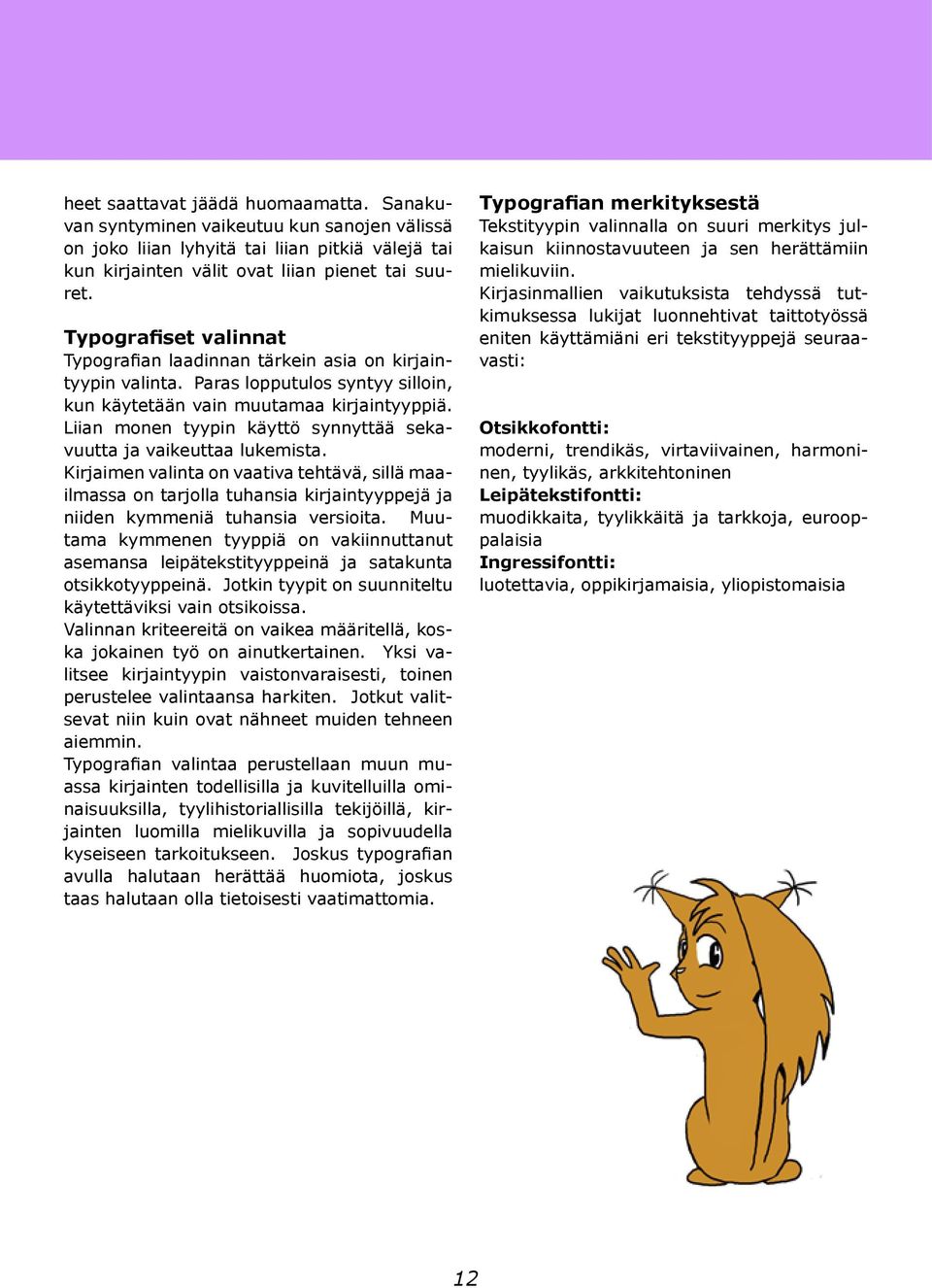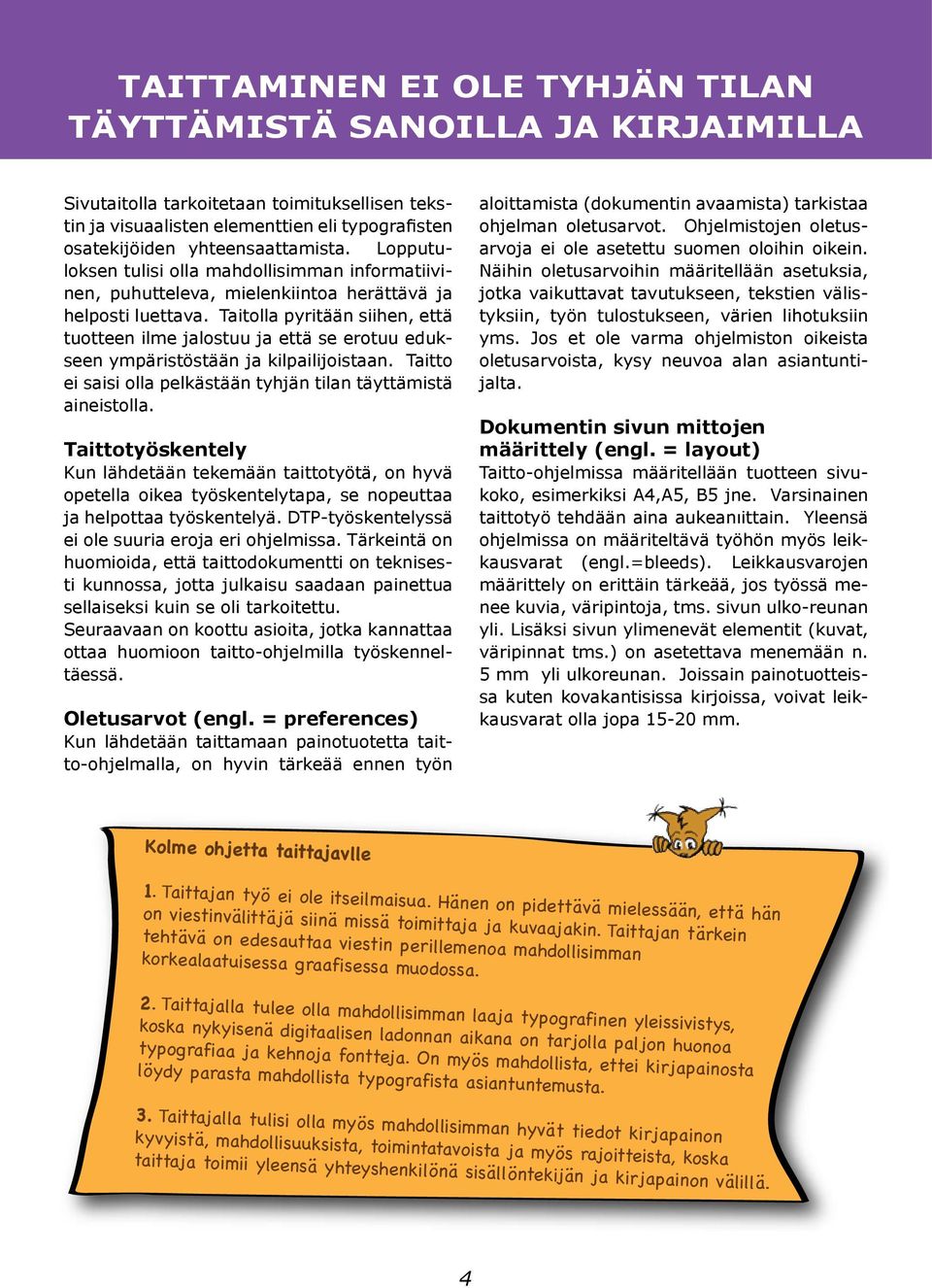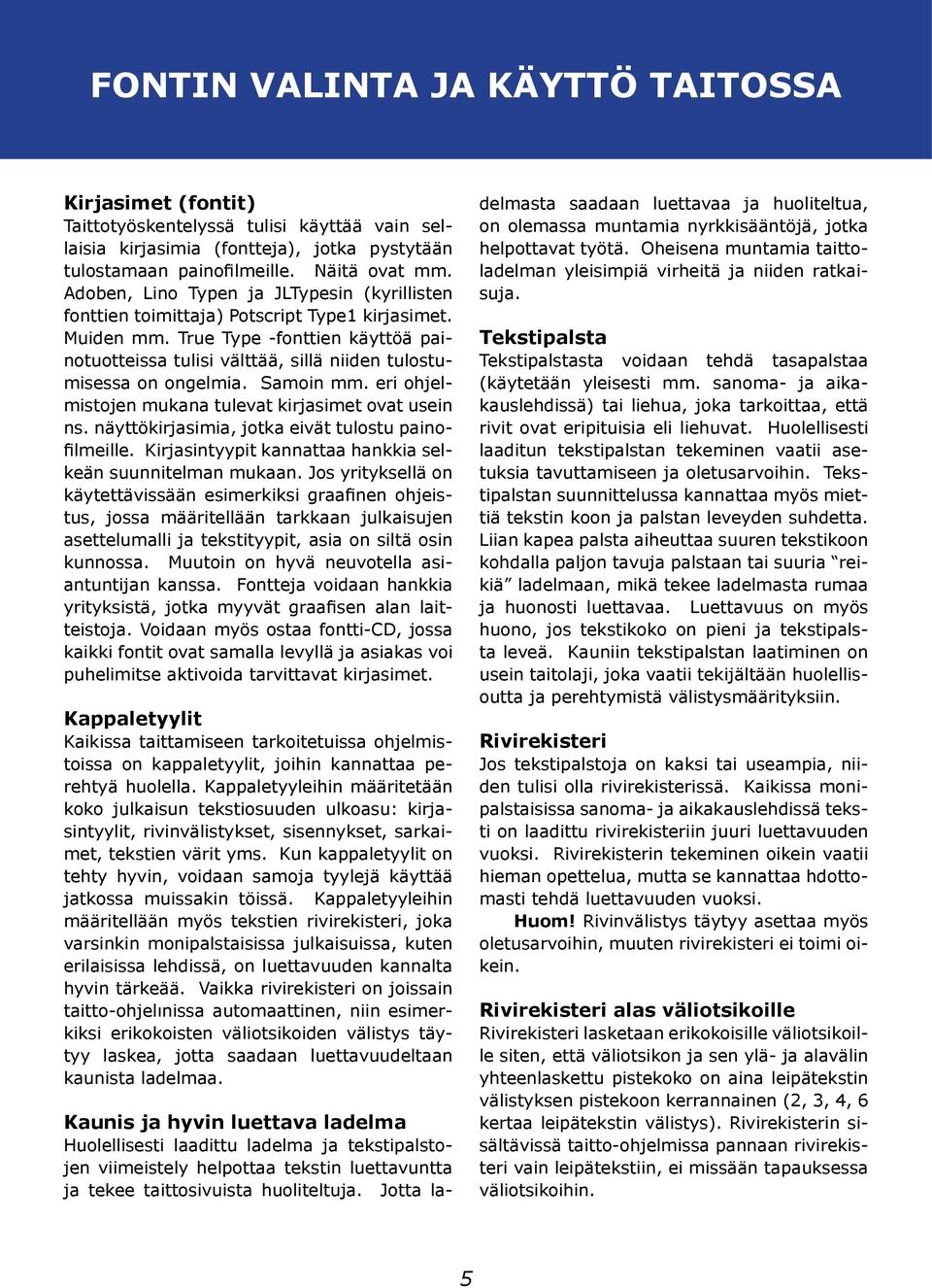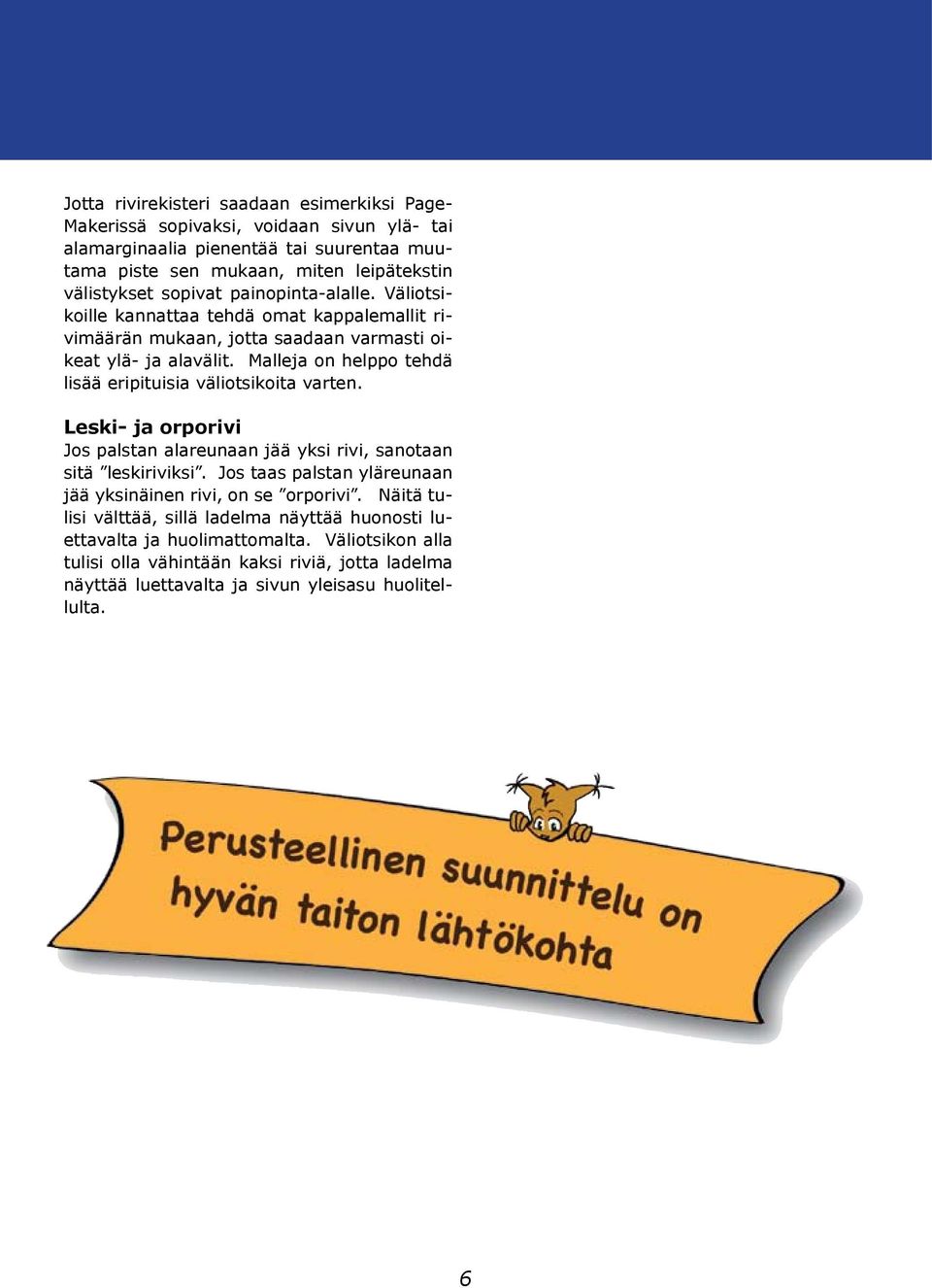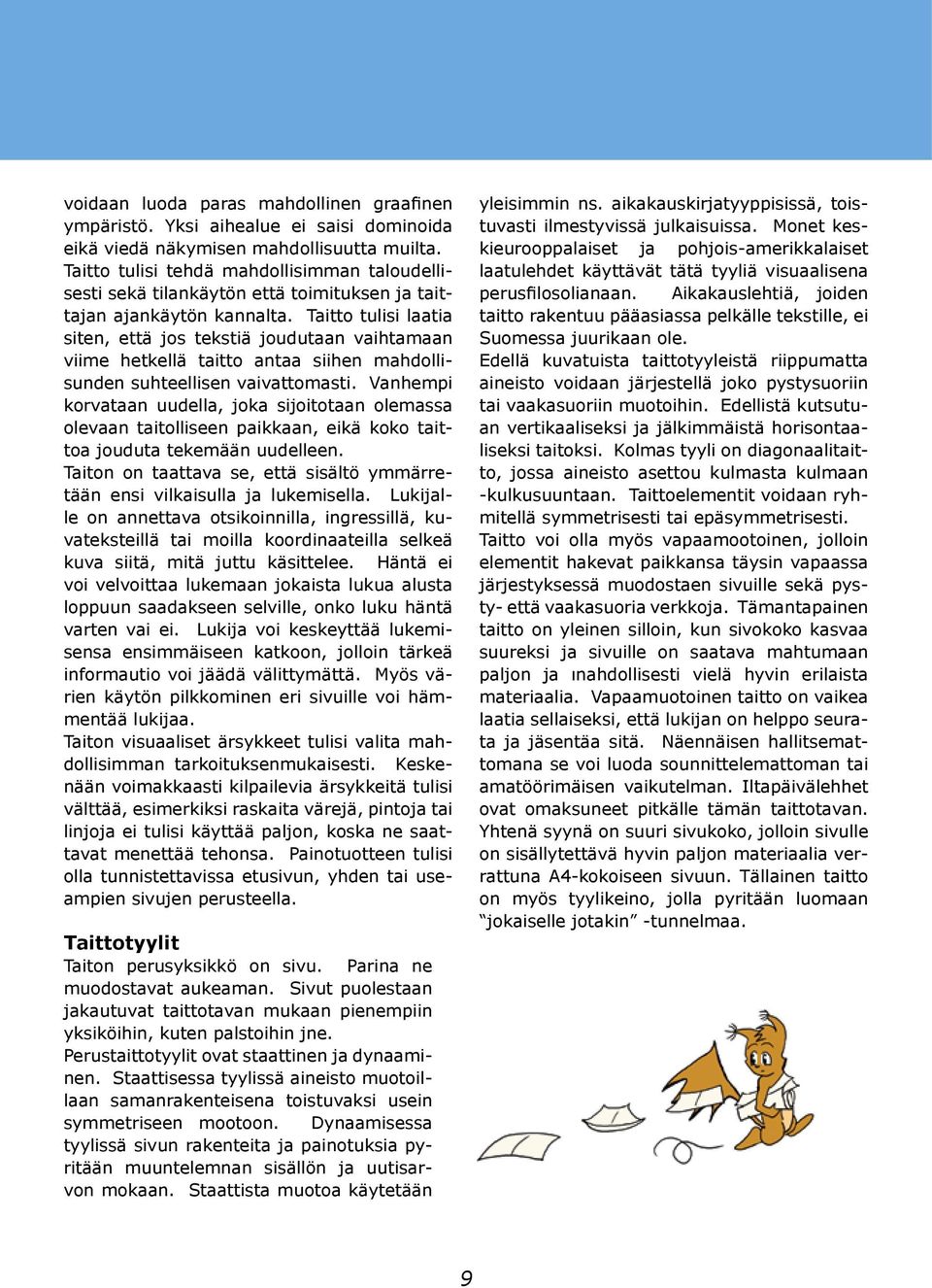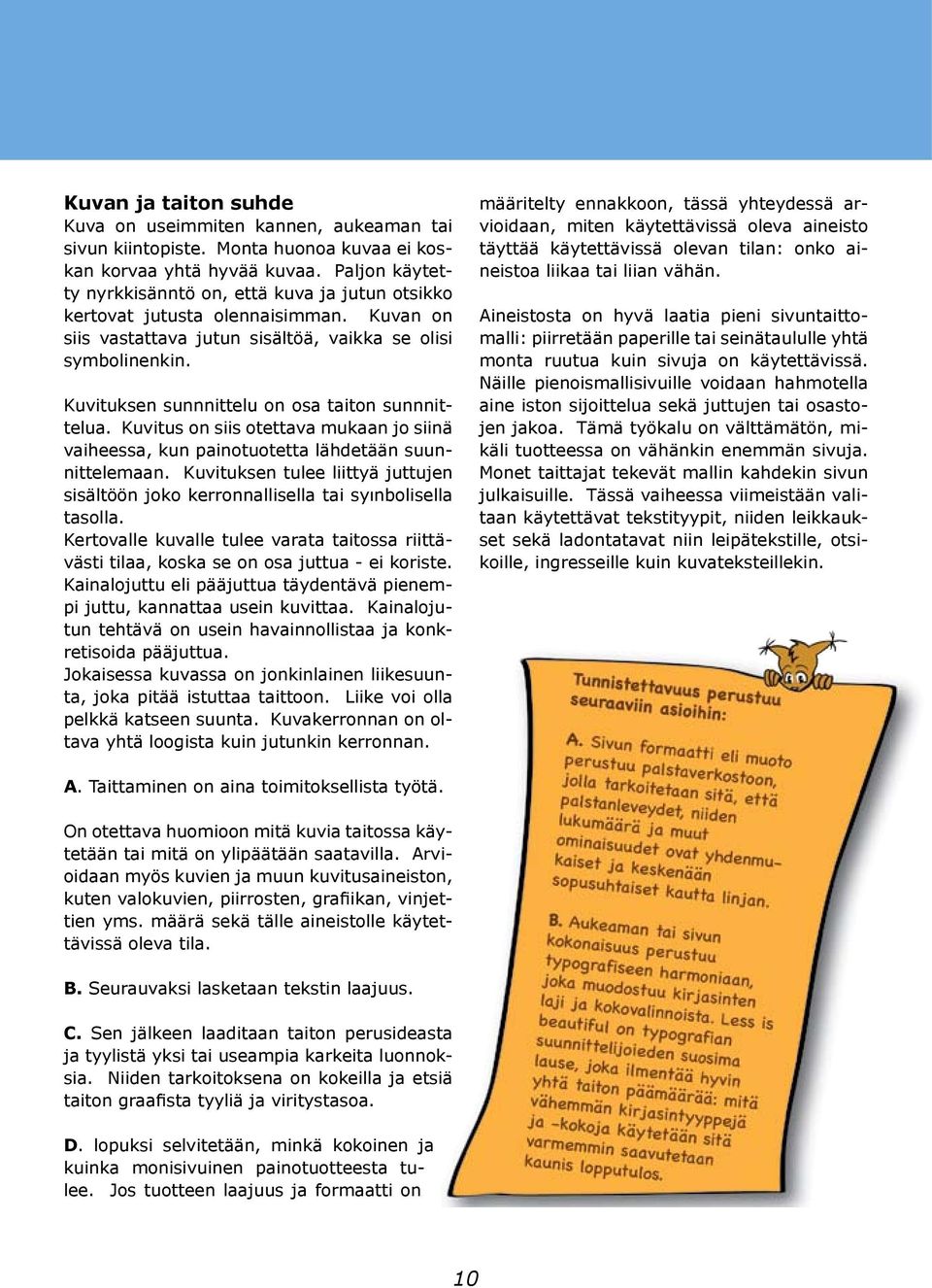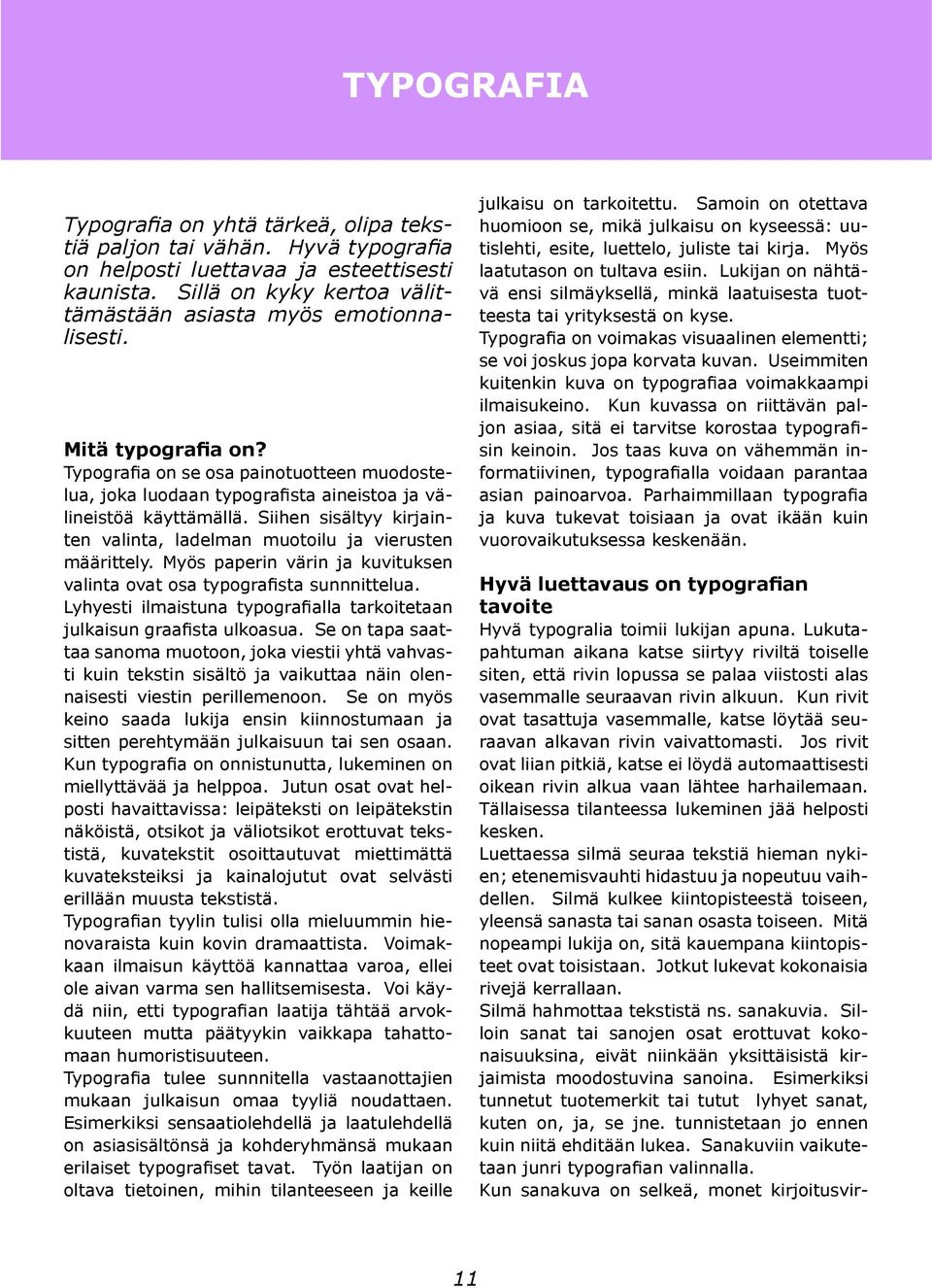
2 TAITTAMINEN EI OLE TYHJÄN TILAN TÄYTTÄMISTÄ SANOILLA JA KIRJAIMILLA Sivutaitolla tarkoitetaan toimituksellisen tekstin ja visuaalisten elementtien eli typografisten osatekijöiden yhteensaattamista. Lopputuloksen tulisi olla mahdollisimman informatiivinen, puhutteleva, mielenkiintoa herättävä ja helposti luettava. Taitolla pyritään siihen, että tuotteen ilme jalostuu ja että se erotuu edukseen ympäristöstään ja kilpailijoistaan. Taitto ei saisi olla pelkästään tyhjän tilan täyttämistä aineistolla. Taittotyöskentely Kun lähdetään tekemään taittotyötä, on hyvä opetella oikea työskentelytapa, se nopeuttaa ja helpottaa työskentelyä. DTP-työskentelyssä ei ole suuria eroja eri ohjelmissa. Tärkeintä on huomioida, että taittodokumentti on teknisesti kunnossa, jotta julkaisu saadaan painettua sellaiseksi kuin se oli tarkoitettu. Seuraavaan on koottu asioita, jotka kannattaa ottaa huomioon taitto-ohjelmilla työskenneltäessä. Oletusarvot (engl. = preferences) Kun lähdetään taittamaan painotuotetta taitto-ohjelmalla, on hyvin tärkeää ennen työn aloittamista (dokumentin avaamista) tarkistaa ohjelman oletusarvot. Ohjelmistojen oletusarvoja ei ole asetettu suomen oloihin oikein. Näihin oletusarvoihin määritellään asetuksia, jotka vaikuttavat tavutukseen, tekstien välistyksiin, työn tulostukseen, värien lihotuksiin yms. Jos et ole varma ohjelmiston oikeista oletusarvoista, kysy neuvoa alan asiantuntijalta. Dokumentin sivun mittojen määrittely (engl. = layout) Taitto-ohjelmissa määritellään tuotteen sivukoko, esimerkiksi A4,A5, B5 jne. Varsinainen taittotyö tehdään aina aukeanıittain. Yleensä ohjelmissa on määriteltävä työhön myös leikkausvarat (engl.=bleeds). Leikkausvarojen määrittely on erittäin tärkeää, jos työssä menee kuvia, väripintoja, tms. sivun ulko-reunan yli. Lisäksi sivun ylimenevät elementit (kuvat, väripinnat tms.) on asetettava menemään n. 5 mm yli ulkoreunan. Joissain painotuotteissa kuten kovakantisissa kirjoissa, voivat leikkausvarat olla jopa mm. Kolme ohjetta taittajavlle 1. Taittajan työ ei ole itseilmaisua. Hänen on pidettävä mielessään, että hän on viestinvälittäjä siinä missä toimittaja ja kuvaajakin. Taittajan tärkein tehtävä on edesauttaa viestin perillemenoa mahdollisimman korkealaatuisessa graafisessa muodossa. 2. Taittajalla tulee olla mahdollisimman laaja typografinen yleissivistys, koska nykyisenä digitaalisen ladonnan aikana on tarjolla paljon huonoa typografiaa ja kehnoja fontteja. On myös mahdollista, ettei kirjapainosta löydy parasta mahdollista typografista asiantuntemusta. 3. Taittajalla tulisi olla myös mahdollisimman hyvät tiedot kirjapainon kyvyistä, mahdollisuuksista, toimintatavoista ja myös rajoitteista, koska taittaja toimii yleensä yhteyshenkilönä sisällöntekijän ja kirjapainon välillä. 4
3 FONTIN VALINTA JA KÄYTTÖ TAITOSSA Kirjasimet (fontit) Taittotyöskentelyssä tulisi käyttää vain sellaisia kirjasimia (fontteja), jotka pystytään tulostamaan painofilmeille. Näitä ovat mm. Adoben, Lino Typen ja JLTypesin (kyrillisten fonttien toimittaja) Potscript Type1 kirjasimet. Muiden mm. True Type -fonttien käyttöä painotuotteissa tulisi välttää, sillä niiden tulostumisessa on ongelmia. Samoin mm. eri ohjelmistojen mukana tulevat kirjasimet ovat usein ns. näyttökirjasimia, jotka eivät tulostu painofilmeille. Kirjasintyypit kannattaa hankkia selkeän suunnitelman mukaan. Jos yrityksellä on käytettävissään esimerkiksi graafinen ohjeistus, jossa määritellään tarkkaan julkaisujen asettelumalli ja tekstityypit, asia on siltä osin kunnossa. Muutoin on hyvä neuvotella asiantuntijan kanssa. Fontteja voidaan hankkia yrityksistä, jotka myyvät graafisen alan laitteistoja. Voidaan myös ostaa fontti-cd, jossa kaikki fontit ovat samalla levyllä ja asiakas voi puhelimitse aktivoida tarvittavat kirjasimet. Kappaletyylit Kaikissa taittamiseen tarkoitetuissa ohjelmistoissa on kappaletyylit, joihin kannattaa perehtyä huolella. Kappaletyyleihin määritetään koko julkaisun tekstiosuuden ulkoasu: kirjasintyylit, rivinvälistykset, sisennykset, sarkaimet, tekstien värit yms. Kun kappaletyylit on tehty hyvin, voidaan samoja tyylejä käyttää jatkossa muissakin töissä. Kappaletyyleihin määritellään myös tekstien rivirekisteri, joka varsinkin monipalstaisissa julkaisuissa, kuten erilaisissa lehdissä, on luettavuuden kannalta hyvin tärkeää. Vaikka rivirekisteri on joissain taitto-ohjelınissa automaattinen, niin esimerkiksi erikokoisten väliotsikoiden välistys täytyy laskea, jotta saadaan luettavuudeltaan kaunista ladelmaa. Kaunis ja hyvin luettava ladelma Huolellisesti laadittu ladelma ja tekstipalstojen viimeistely helpottaa tekstin luettavuntta ja tekee taittosivuista huoliteltuja. Jotta ladelmasta saadaan luettavaa ja huoliteltua, on olemassa muntamia nyrkkisääntöjä, jotka helpottavat työtä. Oheisena muntamia taittoladelman yleisimpiä virheitä ja niiden ratkaisuja. Tekstipalsta Tekstipalstasta voidaan tehdä tasapalstaa (käytetään yleisesti mm. sanoma- ja aikakauslehdissä) tai liehua, joka tarkoittaa, että rivit ovat eripituisia eli liehuvat. Huolellisesti laaditun tekstipalstan tekeminen vaatii asetuksia tavuttamiseen ja oletusarvoihin. Tekstipalstan suunnittelussa kannattaa myös miettiä tekstin koon ja palstan leveyden suhdetta. Liian kapea palsta aiheuttaa suuren tekstikoon kohdalla paljon tavuja palstaan tai suuria reikiä ladelmaan, mikä tekee ladelmasta rumaa ja huonosti luettavaa. Luettavuus on myös huono, jos tekstikoko on pieni ja tekstipalsta leveä. Kauniin tekstipalstan laatiminen on usein taitolaji, joka vaatii tekijältään huolellisoutta ja perehtymistä välistysmäärityksiin. Rivirekisteri Jos tekstipalstoja on kaksi tai useampia, niiden tulisi olla rivirekisterissä. Kaikissa monipalstaisissa sanoma- ja aikakauslehdissä teksti on laadittu rivirekisteriin juuri luettavuuden vuoksi. Rivirekisterin tekeminen oikein vaatii hieman opettelua, mutta se kannattaa hdottomasti tehdä luettavuuden vuoksi. Huom! Rivinvälistys täytyy asettaa myös oletusarvoihin, muuten rivirekisteri ei toimi oikein. Rivirekisteri alas väliotsikoille Rivirekisteri lasketaan erikokoisille väliotsikoille siten, että väliotsikon ja sen ylä- ja alavälin yhteenlaskettu pistekoko on aina leipätekstin välistyksen pistekoon kerrannainen (2, 3, 4, 6 kertaa leipätekstin välistys). Rivirekisterin sisältävissä taitto-ohjelmissa pannaan rivirekisteri vain leipätekstiin, ei missään tapauksessa väliotsikoihin. 5
4 Jotta rivirekisteri saadaan esimerkiksi Page- Makerissä sopivaksi, voidaan sivun ylä- tai alamarginaalia pienentää tai suurentaa muutama piste sen mukaan, miten leipätekstin välistykset sopivat painopinta-alalle. Väliotsikoille kannattaa tehdä omat kappalemallit rivimäärän mukaan, jotta saadaan varmasti oikeat ylä- ja alavälit. Malleja on helppo tehdä lisää eripituisia väliotsikoita varten. Leski- ja orporivi Jos palstan alareunaan jää yksi rivi, sanotaan sitä leskiriviksi. Jos taas palstan yläreunaan jää yksinäinen rivi, on se orporivi. Näitä tulisi välttää, sillä ladelma näyttää huonosti luettavalta ja huolimattomalta. Väliotsikon alla tulisi olla vähintään kaksi riviä, jotta ladelma näyttää luettavalta ja sivun yleisasu huolitellulta. 6
5 TAITTOTYÖ Taittaminen on ennen kaikkea tiedon saattamista lukijalle mahdollisimman tehokkaalla ja miellyttävällä tavalla. Taittotyö tehdään nykyisin yhä useammin tietokoneella. Itse työ on kuitenkin sama riippumatta välineestä. Kone ei tee taittoa eikä anna edes suunnitteluohjeita, vaan se on edelleen sunnnittelijan vastuulla. Seuraavassa taiton perusvaiheet: Sivutaittokaava on 1:1 kokoinen sivun tai aukeaman perusmalli. Siihen piirretään tai merkitään kaikki marginaalit, määritellään palstojen mitat ja paikat, tehdään sivunumeroiden ja muiden mahdollisten taiton elementtien määritykset sekä joissakin tapauksissa myös kuvien leikkausvarat. Tällaisen kaavan avulla taitto pysyy hallinnassa ja johdonmukaisena koko työskentelyn ajan. Taitto-ohjelmalla taitettaessa taittokaavio piirretään muistiin ja 1:1 koossa paperille tai kalvolle. Tälle pohjalle on helppo kokeilla kuvien sijoittelua. Jos pohjasta otetaan kopio, sille on hyvä laatia nopeita pikaluonnoksia. Printattua tai piirrettyä sivutaittokaavaa on hyödyllistä pitää esillä koko taittotyön ajan. Jos perustaittosuunnitemalla tehdään tiimityönä, sivutaittokaava on erittäin hyödyllinen työväline. Sille voidaan hahmotella kaikkien tiimin jäsenten osuudet ja niihin sisältyvien elementtien määrät, paikat, koot ja niiden tarvitsema tila. Taittokaavalle voidaan jo suunnitteluvaiheessa sijoitella tulevien juttujen otsikoita, ingresseja, leipätekstiä, kuvia ja kuvatekstejä. Sivutaittokaavan tulisi sisältää mahdollisimman paljon tietoa tekstityypeistä, ladontatavoista, kuvien koosta, määristä ja värillisyyksistä. Näin tulee tehdä erityisesti silloin, kun taittoa ei laadita taitto-ohielmalla vaan latomolle annetaan ns. saksitaitto ohjeineen. Mistä tekijöistä hyvä taitto syntyy? Painotuotteen ulkoasun tyyli muodostuu typografiasta, kuvista, väreistä, tuotteen formaatista eli muodosta, paperin laadusta ja näiden kaikkien synteesistä. Taitto ei siis ole itsetarkoitus, vaan sen avulla lehden tai jutun sanoman tulisi välittyä lukijalle mahdollisimman tehokkaasti. Kuvien ja tekstin olisi oltava mahdollisimman houkuttelevasti tasapainossa ja vuorovaikutuksessa keskenään. Hyvä taitto takaa informatiivisuuden samalla kun visuaalinen tyyli on sopusoinnussa sisällön kanssa. Tasapaino syntyy monista osatekijöistä. Hyvässä taitossa kuvien osuus kokonaisuudesta ja niiden koko ovat oikeassa suhteessa keskenään. Tekstin ja kuvien välinen suhde vastaa jutun painoarvoa. Visuaalinen tyyli on yhdenmukainen tuotteelle aiemmin luodun ilmeen kanssa, joka puolestaan noudattelee koko yhteisön graafista linjaa tai talotyyliä. Tällöin lukija tunnistaa kunkin painotuotteen osaksi tiettyä kokonaisuutta (ellei ole erityistä syytä tehdä linjasta poikkeavaa tuotetta). -Sesonkitaittamisella tarkoitetaan sitä että painotuotteen taittoa muokataan jossain määrin esimerkiksi vuodenaikojen tai muiden muutosten (esim. vuosipäivä, teema) vuoksi. Vaihtelu voi olla tehokas tapa herättää huomiota, jos linja suunnitellaan ja määritellään etukäteen. Tiettyjen tuttujen elementtien säilyttäminen takaa kuitenkin sen, että tuote on edelleenkin tuttu lukijalleen. Tällaisia elementtejä ovat esimerkiksi formaatti, leipätekstin tai otsikoiden typografia ja palstaleveydet. Lähtötilanne Ennen kuin taittoa lähdetään tekemään tai suunnittelemaan, on hyvä analysoida tilannetta ja tavoitteita. Seuraavat kysymykset auttavat erittelemään työtä ja sen luonnetta. 7
6 Olemus Onko kyseessä kirja (tietokirja, romaani, satukirja), esite (tuote- vai yritysesite), lehti (asiakas-, henkilöstö-, ammattilehti vai jokin muu) vai tuoteluettelo (varastoluettelo vai esite)? Jokaiselle tuotteelle on olemassa tietyt taiton peruslähtökohdat, joita sovelletaan tapauskohtaisesti. Vastaanottajat Onko tuote suunnattu tutulle, homogeeniselle kohderyhmälle vai sellaisille ryhmille, joita kaikkia ei välttämättä edes tunneta? Mikä tahansa erillisryhmä, joka odottaa omaa käsittelytapaa, tulisi ottaa hoomioon taiton ja sisällön suunnittelussa. Pohjaa pohdiskelulle voivat antaa esimerkiksi erilaisten ikä- ja ammattiryhmien lukutottumukset ja odotukset tai eri maantieteellisillä alueilla vallitsevat tavat. Yhteisö voi selvittää nykyisten ja potentiaalisten lukijoiden tiedot, asenteet ja toiveet tutkimuksen avulla, mikä on kaikkein luotettavin lähtökohta julkaisun snunnittelulle. Vastaanottajien käsityksiä ja toiveita voidaan käsitellä erilaisilla foorumeilla, esimerkiksi toimitusneuvostojen ja henkilöstön kokouksissa. Tarkoitus Onko kyse opettamisesta, kouluttamisesta, tiedottamisesta/uutisoinnista, taustoittamisesta, vaikuttamisesta/ yrityksen profiloinnista, markkinoinnista vai myynnistä? Paitsi että sisältö vaihtelee tuotteen tarkoituksen mukaan myös ulkoasun on vastattava tarkoitustaan. Resurssit Mitkä ovat käytettävissä olevat aineelliset ja henkiset resurssit eli voimavarat sekä tilaajan että toteuttajien puolella: raha, tiedot, taidot, tekniikka, olemassa oleva tuotteeseen sopiva materiaali, kuten kuvat, grafiikka tai muu kuvitusmateriaali? Lisäksi on oltava tietoinen käytössä olevista graafisen teknologian mahdollisuuksista ja toisaalta rajoitteista, joita ovat esimerkiksi suurimmat ja pienimmät mahdolliset formaatit, värisyydet, käytettävissä olevien paperilaatujen kirjo jne. Selvitä onko kyseessä kertatuote vai jatkuvasti ilmestyvä julkaisu. Joskus on myös tarpeen tarkistaa, onko tuleva julkaisu osa jotakin aiempaa sarjaa tai käytäntöä, joka luo omat ehtonsa (esim. formaatin, värityksen, sidonnan, paperin jue. suhteen) vai aloittaako julkaisu uuden sarjan ja uudet käytännöt. Aikataulu Alusta lähtien on oltava tiedossa aikataulu, joka vaikuttaa paitsi suunnitteluprosessiin myös edellisen kohdan resurssien tarpeeseen. Jos taitto sunnnitellaan alusta lähtien, tarvitaan luonnollisesti enemmän aikaa kuin vakiintuneen julkaisun taittoon. Asema Mille markkinoille tuote on tulossa, millaisia kilpailijoita on, mikä on tuotteen asema markkinoilla? Halutaanko sen sulautuvan joukkoon vai pyritäänkö erottumaan muista? Lähtötilanteen selvittäminen kuuluu myös painotuotteen asemointiyhteisön muuhun viestintään. Miten eri toimenpiteet ajoittuvat, mitä sisältöjä niillä on ja miltä ne näyttävat? Tavoitteet Uutta tai jo olemassa olevaa painotuotetta ja sen taittoa suunniteltaessa on aina hyödyllistä arvioida edellinen julkaisu - sen hyvät ja huonot puolet. Niiden pohjalta uuden julkaisun tavoitteet syntyvät tavallaan itsestään. Entisiä virheitä ei varmaankaan haluta toistaa, ja parannusehdotukset pyritään täyttämään. Painotuotteen kokonaisuudelta vaaditaan yleensä kykyä välittää sisältämänsä informaatio mahdollisimman hyvin. Jo alkuperäisessä suunnitelmassa tulisi ottaa huomioon kaikki ne aiheet ja teemat, joita julkaisussa käsitellään. Mahdollisouksien mukaan tulisi ennakoida niitä alueita tai teemoja, joita mahdollisesti tulevaisundessa tullaan käsittelemään. Näin niille 8
7 voidaan luoda paras mahdollinen graafinen ympäristö. Yksi aihealue ei saisi dominoida eikä viedä näkymisen mahdollisuutta muilta. Taitto tulisi tehdä mahdollisimman taloudellisesti sekä tilankäytön että toimituksen ja taittajan ajankäytön kannalta. Taitto tulisi laatia siten, että jos tekstiä joudutaan vaihtamaan viime hetkellä taitto antaa siihen mahdollisunden suhteellisen vaivattomasti. Vanhempi korvataan uudella, joka sijoitotaan olemassa olevaan taitolliseen paikkaan, eikä koko taittoa jouduta tekemään uudelleen. Taiton on taattava se, että sisältö ymmärretään ensi vilkaisulla ja lukemisella. Lukijalle on annettava otsikoinnilla, ingressillä, kuvateksteillä tai moilla koordinaateilla selkeä kuva siitä, mitä juttu käsittelee. Häntä ei voi velvoittaa lukemaan jokaista lukua alusta loppuun saadakseen selville, onko luku häntä varten vai ei. Lukija voi keskeyttää lukemisensa ensimmäiseen katkoon, jolloin tärkeä informautio voi jäädä välittymättä. Myös värien käytön pilkkominen eri sivuille voi hämmentää lukijaa. Taiton visuaaliset ärsykkeet tulisi valita mahdollisimman tarkoituksenmukaisesti. Keskenään voimakkaasti kilpailevia ärsykkeitä tulisi välttää, esimerkiksi raskaita värejä, pintoja tai linjoja ei tulisi käyttää paljon, koska ne saattavat menettää tehonsa. Painotuotteen tulisi olla tunnistettavissa etusivun, yhden tai useampien sivujen perusteella. Taittotyylit Taiton perusyksikkö on sivu. Parina ne muodostavat aukeaman. Sivut puolestaan jakautuvat taittotavan mukaan pienempiin yksiköihin, kuten palstoihin jne. Perustaittotyylit ovat staattinen ja dynaaminen. Staattisessa tyylissä aineisto muotoillaan samanrakenteisena toistuvaksi usein symmetriseen mootoon. Dynaamisessa tyylissä sivun rakenteita ja painotuksia pyritään muuntelemnan sisällön ja uutisarvon mokaan. Staattista muotoa käytetään yleisimmin ns. aikakauskirjatyyppisissä, toistuvasti ilmestyvissä julkaisuissa. Monet keskieurooppalaiset ja pohjois-amerikkalaiset laatulehdet käyttävät tätä tyyliä visuaalisena perusfilosolianaan. Aikakauslehtiä, joiden taitto rakentuu pääasiassa pelkälle tekstille, ei Suomessa juurikaan ole. Edellä kuvatuista taittotyyleistä riippumatta aineisto voidaan järjestellä joko pystysuoriin tai vaakasuoriin muotoihin. Edellistä kutsutuan vertikaaliseksi ja jälkimmäistä horisontaaliseksi taitoksi. Kolmas tyyli on diagonaalitaitto, jossa aineisto asettou kulmasta kulmaan -kulkusuuntaan. Taittoelementit voidaan ryhmitellä symmetrisesti tai epäsymmetrisesti. Taitto voi olla myös vapaamootoinen, jolloin elementit hakevat paikkansa täysin vapaassa järjestyksessä muodostaen sivuille sekä pysty- että vaakasuoria verkkoja. Tämantapainen taitto on yleinen silloin, kun sivokoko kasvaa suureksi ja sivuille on saatava mahtumaan paljon ja ınahdollisesti vielä hyvin erilaista materiaalia. Vapaamuotoinen taitto on vaikea laatia sellaiseksi, että lukijan on helppo seurata ja jäsentäa sitä. Näennäisen hallitsemattomana se voi luoda sounnittelemattoman tai amatöörimäisen vaikutelman. Iltapäivälehhet ovat omaksuneet pitkälle tämän taittotavan. Yhtenä syynä on suuri sivukoko, jolloin sivulle on sisällytettävä hyvin paljon materiaalia verrattuna A4-kokoiseen sivuun. Tällainen taitto on myös tyylikeino, jolla pyritään luomaan jokaiselle jotakin -tunnelmaa. 9
8 Kuvan ja taiton suhde Kuva on useimmiten kannen, aukeaman tai sivun kiintopiste. Monta huonoa kuvaa ei koskan korvaa yhtä hyvää kuvaa. Paljon käytetty nyrkkisänntö on, että kuva ja jutun otsikko kertovat jutusta olennaisimman. Kuvan on siis vastattava jutun sisältöä, vaikka se olisi symbolinenkin. Kuvituksen sunnnittelu on osa taiton sunnnittelua. Kuvitus on siis otettava mukaan jo siinä vaiheessa, kun painotuotetta lähdetään suunnittelemaan. Kuvituksen tulee liittyä juttujen sisältöön joko kerronnallisella tai syınbolisella tasolla. Kertovalle kuvalle tulee varata taitossa riittävästi tilaa, koska se on osa juttua - ei koriste. Kainalojuttu eli pääjuttua täydentävä pienempi juttu, kannattaa usein kuvittaa. Kainalojutun tehtävä on usein havainnollistaa ja konkretisoida pääjuttua. Jokaisessa kuvassa on jonkinlainen liikesuunta, joka pitää istuttaa taittoon. Liike voi olla pelkkä katseen suunta. Kuvakerronnan on oltava yhtä loogista kuin jutunkin kerronnan. määritelty ennakkoon, tässä yhteydessä arvioidaan, miten käytettävissä oleva aineisto täyttää käytettävissä olevan tilan: onko aineistoa liikaa tai liian vähän. Aineistosta on hyvä laatia pieni sivuntaittomalli: piirretään paperille tai seinätaululle yhtä monta ruutua kuin sivuja on käytettävissä. Näille pienoismallisivuille voidaan hahmotella aine iston sijoittelua sekä juttujen tai osastojen jakoa. Tämä työkalu on välttämätön, mikäli tuotteessa on vähänkin enemmän sivuja. Monet taittajat tekevät mallin kahdekin sivun julkaisuille. Tässä vaiheessa viimeistään valitaan käytettävat tekstityypit, niiden leikkaukset sekä ladontatavat niin leipätekstille, otsikoille, ingresseille kuin kuvateksteillekin. A. Taittaminen on aina toimitoksellista työtä. On otettava huomioon mitä kuvia taitossa käytetään tai mitä on ylipäätään saatavilla. Arvioidaan myös kuvien ja muun kuvitusaineiston, kuten valokuvien, piirrosten, grafiikan, vinjettien yms. määrä sekä tälle aineistolle käytettävissä oleva tila. B. Seurauvaksi lasketaan tekstin laajuus. C. Sen jälkeen laaditaan taiton perusideasta ja tyylistä yksi tai useampia karkeita luonnoksia. Niiden tarkoitoksena on kokeilla ja etsiä taiton graafista tyyliä ja viritystasoa. D. lopuksi selvitetään, minkä kokoinen ja kuinka monisivuinen painotuotteesta tulee. Jos tuotteen laajuus ja formaatti on 10
9 TYPOGRAFIA Typografia on yhtä tärkeä, olipa tekstiä paljon tai vähän. Hyvä typografia on helposti luettavaa ja esteettisesti kaunista. Sillä on kyky kertoa välittämästään asiasta myös emotionnalisesti. Mitä typografia on? Typografia on se osa painotuotteen muodostelua, joka luodaan typografista aineistoa ja välineistöä käyttämällä. Siihen sisältyy kirjainten valinta, ladelman muotoilu ja vierusten määrittely. Myös paperin värin ja kuvituksen valinta ovat osa typografista sunnnittelua. Lyhyesti ilmaistuna typografialla tarkoitetaan julkaisun graafista ulkoasua. Se on tapa saattaa sanoma muotoon, joka viestii yhtä vahvasti kuin tekstin sisältö ja vaikuttaa näin olennaisesti viestin perillemenoon. Se on myös keino saada lukija ensin kiinnostumaan ja sitten perehtymään julkaisuun tai sen osaan. Kun typografia on onnistunutta, lukeminen on miellyttävää ja helppoa. Jutun osat ovat helposti havaittavissa: leipäteksti on leipätekstin näköistä, otsikot ja väliotsikot erottuvat tekstistä, kuvatekstit osoittautuvat miettimättä kuvateksteiksi ja kainalojutut ovat selvästi erillään muusta tekstistä. Typografian tyylin tulisi olla mieluummin hienovaraista kuin kovin dramaattista. Voimakkaan ilmaisun käyttöä kannattaa varoa, ellei ole aivan varma sen hallitsemisesta. Voi käydä niin, etti typografian laatija tähtää arvokkuuteen mutta päätyykin vaikkapa tahattomaan humoristisuuteen. Typografia tulee sunnnitella vastaanottajien mukaan julkaisun omaa tyyliä noudattaen. Esimerkiksi sensaatiolehdellä ja laatulehdellä on asiasisältönsä ja kohderyhmänsä mukaan erilaiset typografiset tavat. Työn laatijan on oltava tietoinen, mihin tilanteeseen ja keille julkaisu on tarkoitettu. Samoin on otettava huomioon se, mikä julkaisu on kyseessä: uutislehti, esite, luettelo, juliste tai kirja. Myös laatutason on tultava esiin. Lukijan on nähtävä ensi silmäyksellä, minkä laatuisesta tuotteesta tai yrityksestä on kyse. Typografia on voimakas visuaalinen elementti; se voi joskus jopa korvata kuvan. Useimmiten kuitenkin kuva on typografiaa voimakkaampi ilmaisukeino. Kun kuvassa on riittävän paljon asiaa, sitä ei tarvitse korostaa typografisin keinoin. Jos taas kuva on vähemmän informatiivinen, typografialla voidaan parantaa asian painoarvoa. Parhaimmillaan typografia ja kuva tukevat toisiaan ja ovat ikään kuin vuorovaikutuksessa keskenään. Hyvä luettavaus on typografian tavoite Hyvä typogralia toimii lukijan apuna. Lukutapahtuman aikana katse siirtyy riviltä toiselle siten, että rivin lopussa se palaa viistosti alas vasemmalle seuraavan rivin alkuun. Kun rivit ovat tasattuja vasemmalle, katse löytää seuraavan alkavan rivin vaivattomasti. Jos rivit ovat liian pitkiä, katse ei löydä automaattisesti oikean rivin alkua vaan lähtee harhailemaan. Tällaisessa tilanteessa lukeminen jää helposti kesken. Luettaessa silmä seuraa tekstiä hieman nykien; etenemisvauhti hidastuu ja nopeutuu vaihdellen. Silmä kulkee kiintopisteestä toiseen, yleensä sanasta tai sanan osasta toiseen. Mitä nopeampi lukija on, sitä kauempana kiintopisteet ovat toisistaan. Jotkut lukevat kokonaisia rivejä kerrallaan. Silmä hahmottaa tekstistä ns. sanakuvia. Silloin sanat tai sanojen osat erottuvat kokonaisuuksina, eivät niinkään yksittäisistä kirjaimista moodostuvina sanoina. Esimerkiksi tunnetut tuotemerkit tai tutut lyhyet sanat, kuten on, ja, se jne. tunnistetaan jo ennen kuin niitä ehditään lukea. Sanakuviin vaikutetaan junri typografian valinnalla. Kun sanakuva on selkeä, monet kirjoitusvir- 11
10 heet saattavat jäädä huomaamatta. Sanakuvan syntyminen vaikeutuu kun sanojen välissä on joko liian lyhyitä tai liian pitkiä välejä tai kun kirjainten välit ovat liian pienet tai suuret. Typografiset valinnat Typografian laadinnan tärkein asia on kirjaintyypin valinta. Paras lopputulos syntyy silloin, kun käytetään vain muutamaa kirjaintyyppiä. Liian monen tyypin käyttö synnyttää sekavuutta ja vaikeuttaa lukemista. Kirjaimen valinta on vaativa tehtävä, sillä maailmassa on tarjolla tuhansia kirjaintyyppejä ja niiden kymmeniä tuhansia versioita. Muutama kymmenen tyyppiä on vakiinnuttanut asemansa leipätekstityyppeinä ja satakunta otsikkotyyppeinä. Jotkin tyypit on suunniteltu käytettäviksi vain otsikoissa. Valinnan kriteereitä on vaikea määritellä, koska jokainen työ on ainutkertainen. Yksi valitsee kirjaintyypin vaistonvaraisesti, toinen perustelee valintaansa harkiten. Jotkut valitsevat niin kuin ovat nähneet muiden tehneen aiemmin. Typografian valintaa perustellaan muun muassa kirjainten todellisilla ja kuvitelluilla ominaisuuksilla, tyylihistoriallisilla tekijöillä, kirjainten luomilla mielikuvilla ja sopivuudella kyseiseen tarkoitukseen. Joskus typografian avulla halutaan herättää huomiota, joskus taas halutaan olla tietoisesti vaatimattomia. Typografian merkityksestä Tekstityypin valinnalla on suuri merkitys julkaisun kiinnostavuuteen ja sen herättämiin mielikuviin. Kirjasinmallien vaikutuksista tehdyssä tutkimuksessa lukijat luonnehtivat taittotyössä eniten käyttämiäni eri tekstityyppejä seuraavasti: Otsikkofontti: moderni, trendikäs, virtaviivainen, harmoninen, tyylikäs, arkkitehtoninen Leipätekstifontti: muodikkaita, tyylikkäitä ja tarkkoja, eurooppalaisia Ingressifontti: luotettavia, oppikirjamaisia, yliopistomaisia 12
11 Lähteet: HIETALA, VEIJO (1996): Kuvien todellisuus, BTJ Kirjastopalvelu Oy, Hclsinki. HUOVILA, TAPANI (1996): Layout as a message. Gummerus Kirjapaino Oy, Saarijärvi. HURTBURT, ALLEN (1989): Layout. The Design of the Printed Page. New York. ELISA JUHOLIN 1999: Visuaalisen viestinnän käsikirja, Jyväskylä ONG, WALTER (1988): Orality and Literacy. London and New York. Routledge. POIKOLAINEN, LIISA (toim.) (1994): Design Management. Otava, Keuruu. SONTAG, SUSAN (1984): Valokuvaukscsta. Love Kirjat, Helsinki. TARASTI, EERO (1996): Johdatusta semiotiikkaan. Oy Gaudeamus, Helsinki. MILLA TORO (1999): DTP & painotyö, Porvoo UIMONEN, RISTO JA IKÄVALKO, ELI- SA (1996): Mielikuvien maailma. Inforviestintä Oy, Helsinki. 13